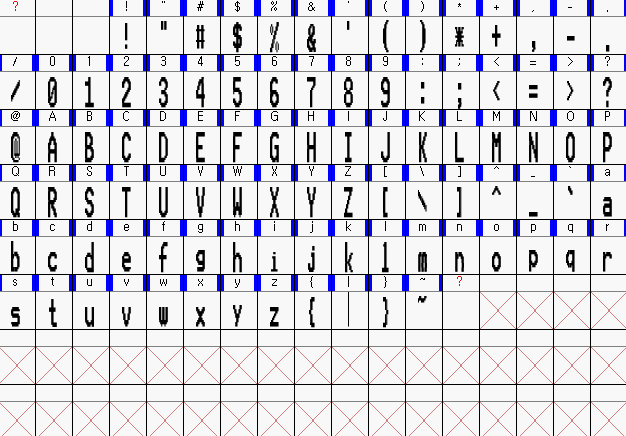
bitMatrix-E1-narrow
bitMatrix-E1 family fonts are often used by some banks to print the POS receipts.
Contoh hasil cetak 4 (AXIS Bank) (①bitMatrix-E1 ②bitMatrix-E1-narrow):
Contoh hasil cetak 6 (Citibank) (①bitMatrix-E1 ②bitMatrix-E1-narrow):
Contoh hasil cetak 8 (①bitMatrix-E1-narrow):
Contoh hasil cetak 9 (①bitMatrix-E1-narrow):
Contoh hasil cetak 10 (①bitMatrix-E1-narrow):
Contoh hasil cetak 17 (①bitMatrix-E1-narrow):
Semua karakter font bitMatrix-E1-narrow:
Font bitMatrix-E1-narrow dilihat dengan penampil font bawaan Windows: